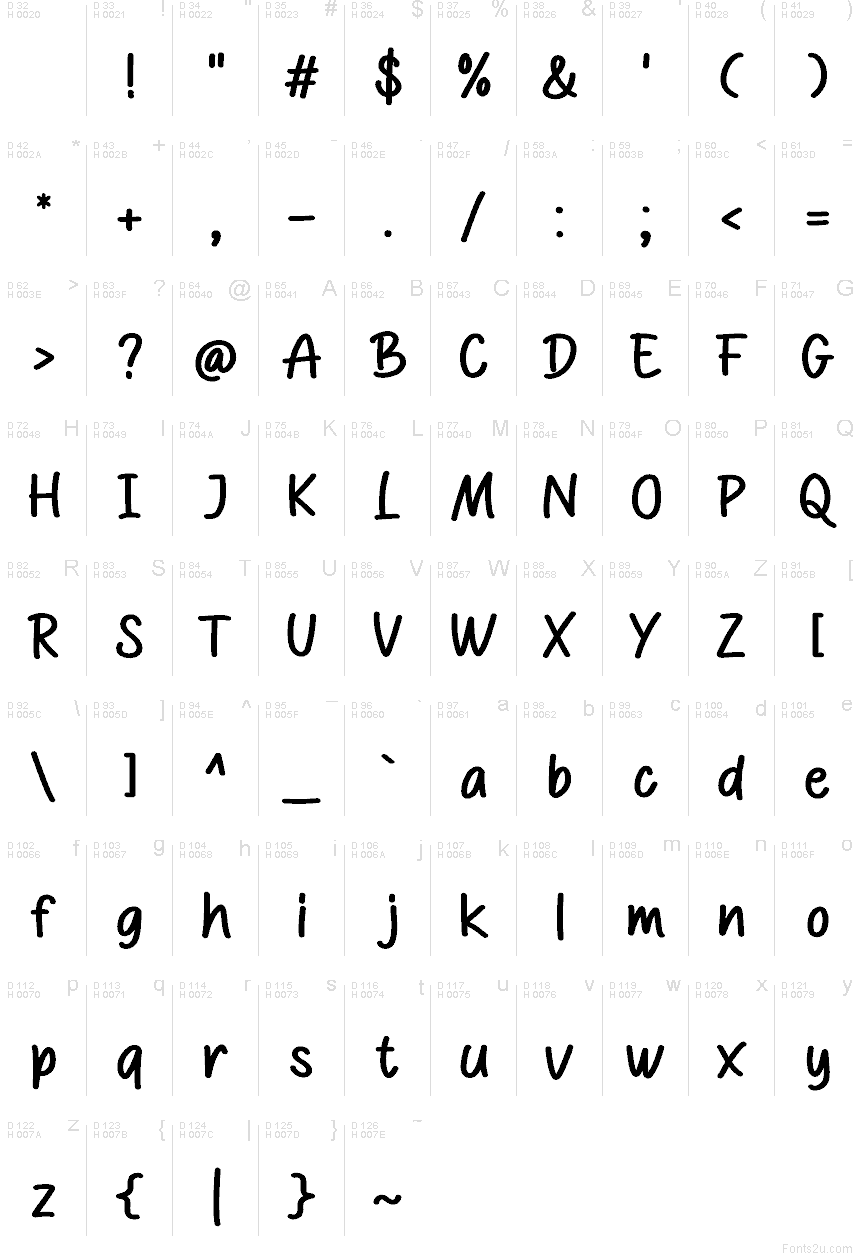
Comic Real هو خط مجاني مكتوب بخط اليد يتميز بضربات عالية ومستديرة، ويضفي إيقاعاً انسيابياً وعفوياً. تحافظ الحروف على بساطة قصص الكوميكس، مع منحنيات مفتوحة، ووصلات ناعمة، وخطوط مريحة تبدو وكأنها مرسومة باليد بدلاً من كونها مصممة رقمياً.
يعد Comic Real مثالياً لكتب الأطفال، والقصص المصورة، ورسومات وسائل التواصل الاجتماعي، والملصقات، وملصقات المنتجات، وأي علامة تجارية غير رسمية تبحث عن تلك اللمسة الودودة والمصنوعة يدوياً. يضيف هذا الخط المجاني لمسة شخصية خفيفة على الدعوات، والاقتباسات، والتغليف، والنصوص القصيرة، دون أن يبدو معقداً أو رسمياً بشكل مبالغ فيه.